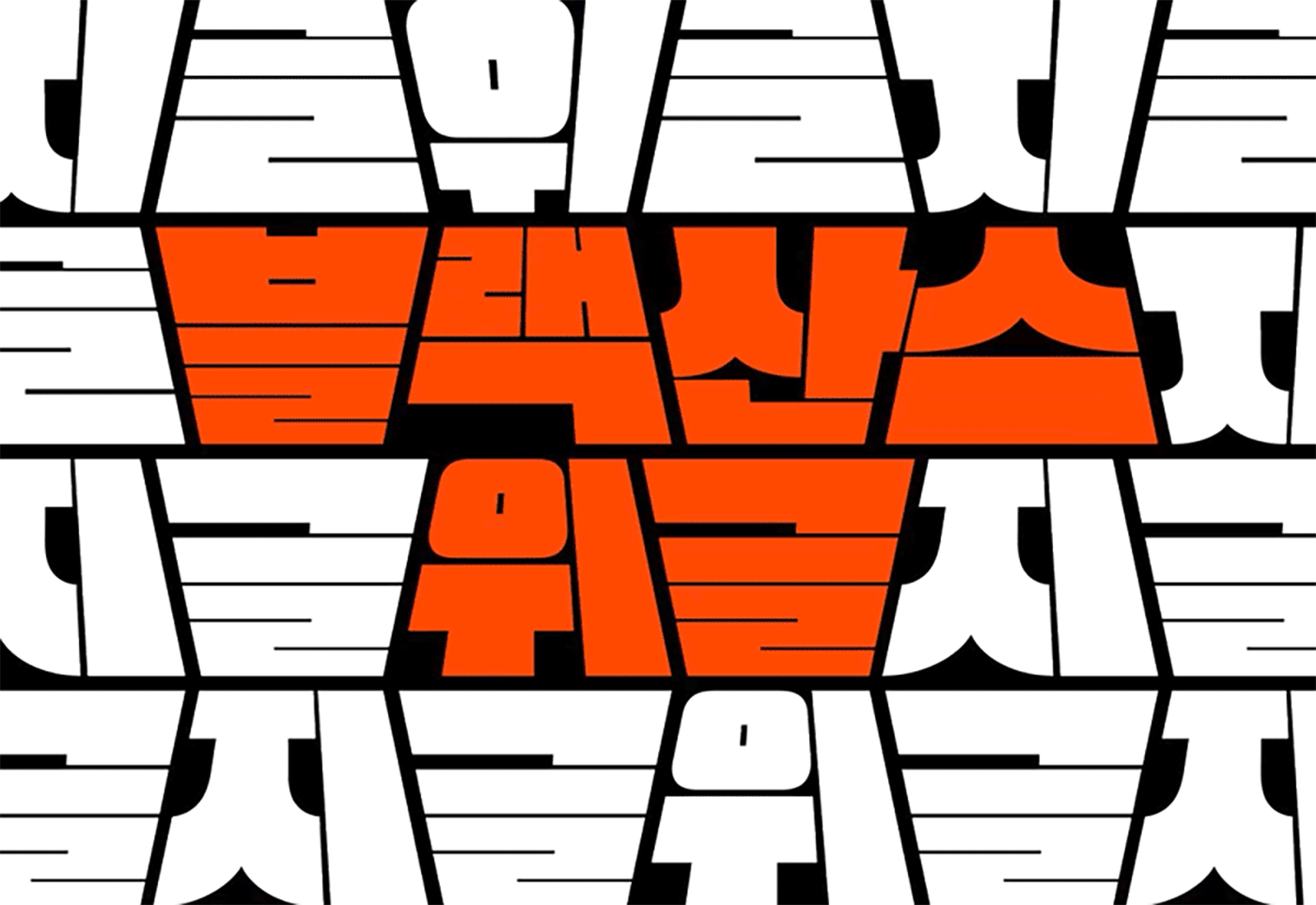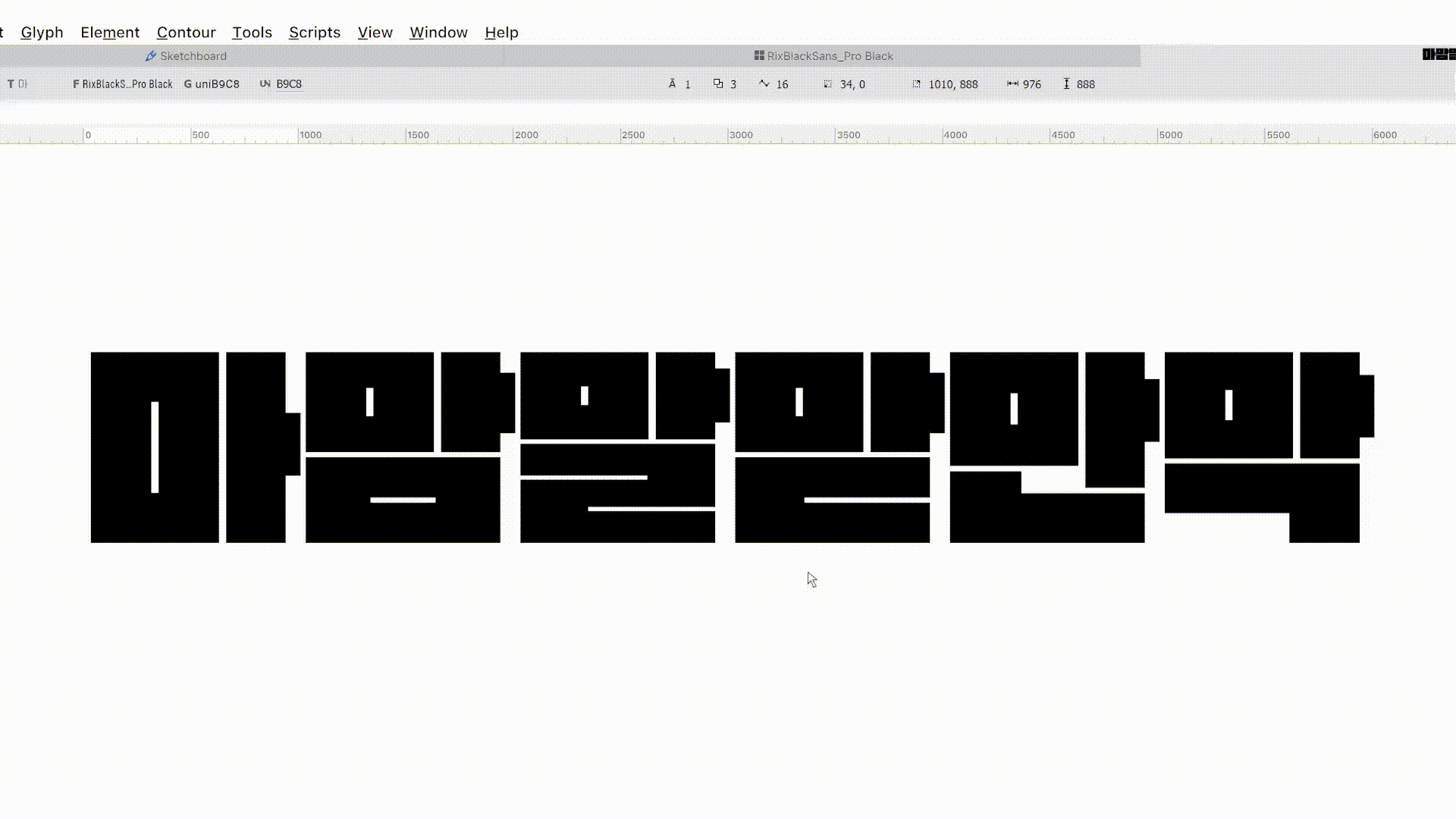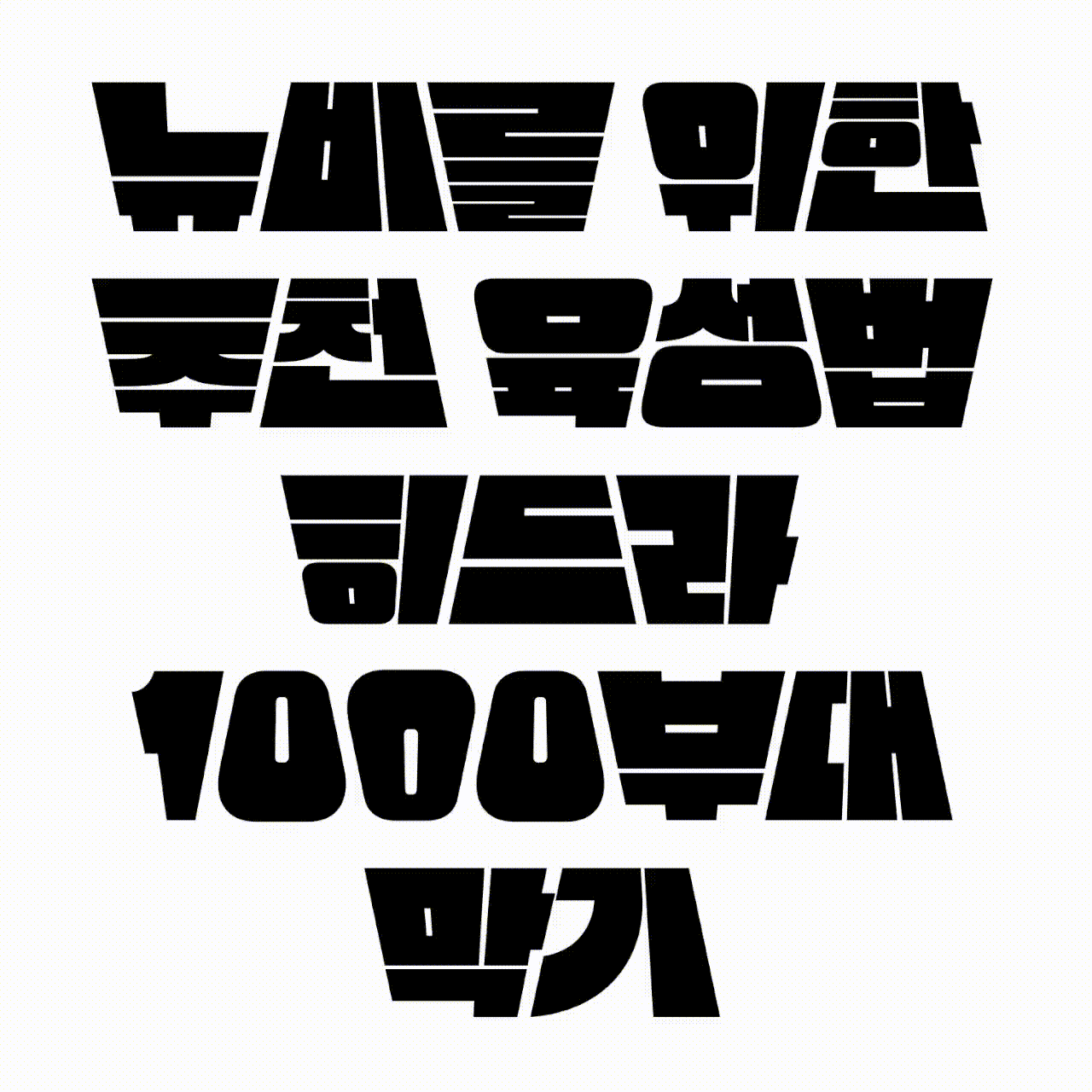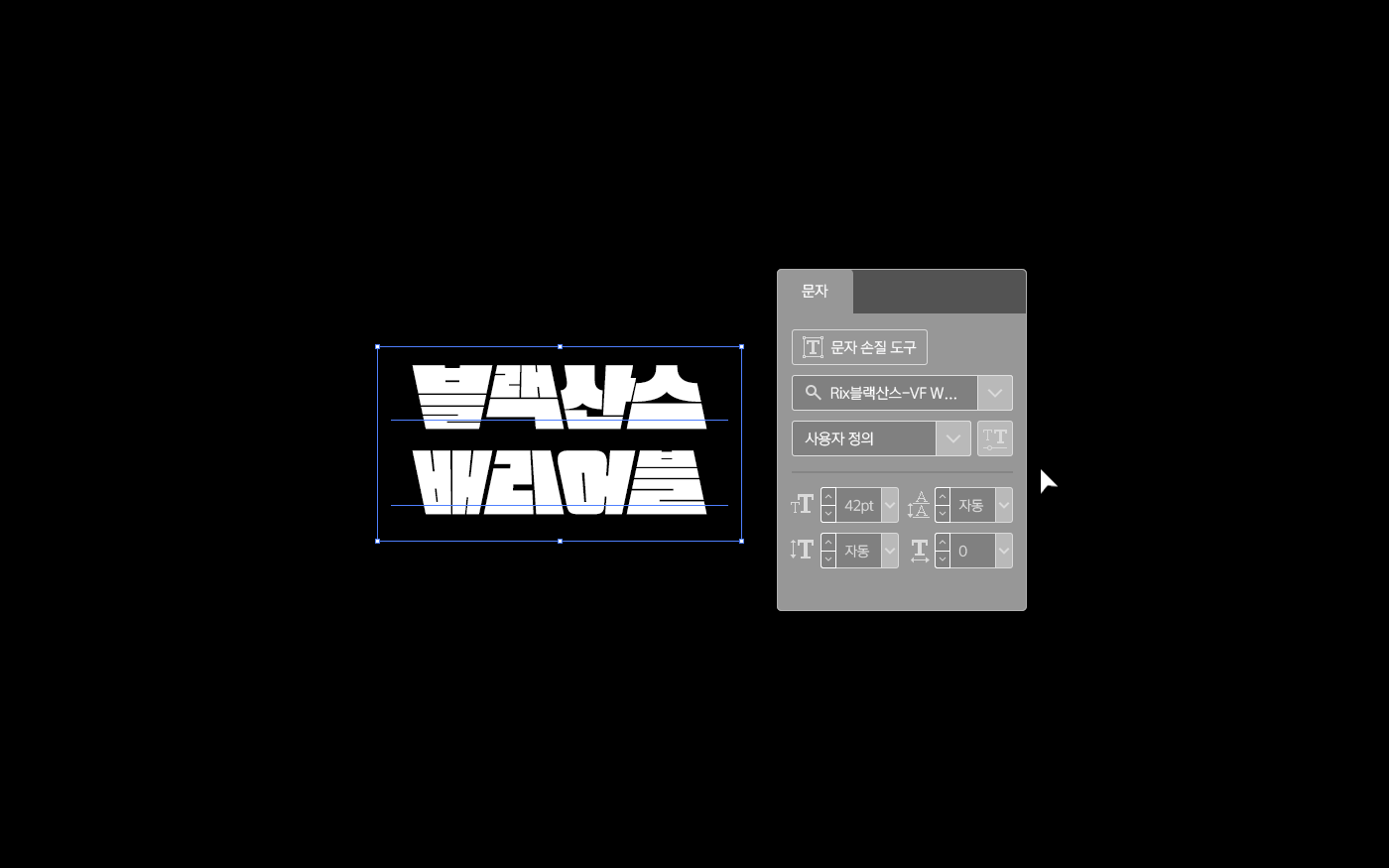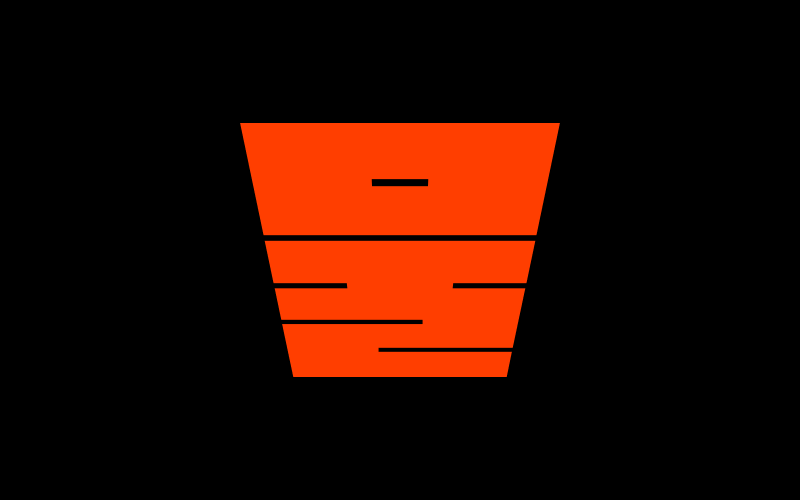
안녕하세요. 오늘은 위트 있고 강렬한 매력을 가진! 10월의 신서체「Rix블랙산스-VF Wiggle」을 소개합니다. 제목용 서체로 여전히 많은 사랑을 받고 있는 Rix블랙산스에서 변형을 준 서체인데요. 배리어블 축을 통해 사용자가 직접 글자의 속성을 조절하여 하나의 폰트로 다양한 형태를 구현할 수 있는 폰트입니다. 이번 블랙산스배리어블의 제작을 맡으신 박민우 디자이너와의 인터뷰를 통해 폰트에 대해 더 자세히 알아볼게요 :)
안녕하세요! 이번 10월 신서체 Rix블랙산스배리어블 Wiggle을 담당한 박민우입니다. 처음 인사드리네요!
처음으로 제작을 맡으신 폰트라고 들었어요. 어떤 과정이 있었나요?
네 맞습니다, 시작은 동료 디자이너님이 제작한 Rix힘을내요 였습니다. 역삼각형 글자 틀이 재미있는 폰트인데, 보다 보니 이 기울기가 한 방향이 아니라 반대 방향으로 번갈아 반복된다면 개성 있는 인상을 줄 것 같다는 영감을 받았거든요. 발상을 한 뒤로 Opentype 기능을 공부하며 고민하다가, Opentype 문맥 대체 기능을 활용해 구현이 가능함을 확인하고 작업을 시작했습니다. 변형되는 글자 틀을 강조해서 보여주기 위해 네모 틀에 꽉꽉 들어찬 모듈의 Rix블랙산스를 베이스로 선택했고, 파이썬으로 글리프의 활자면 자체에 원근 변환을 주어 외곽선을 조정하는 스크립트를 개발했습니다. 스크립트 적용 이후 라틴과 약물 오류를 수정해 디자인을 마무리했습니다.
Rix블랙산스-VF Wiggle 폰트에 대해 더 자세히 알려주세요!
Rix블랙산스-VF Wiggle은 반대 기울기의 사다리꼴 글자 틀이 번갈아 가며 타이핑되는 특이한 인상의 폰트입니다. 블랙산스의 까맣고 묵직한 인상을 유지하면서도, 들쑥날쑥한 기울기가 만드는 리듬감으로 눈길을 끄는 재미있는 글줄을 만들 수 있습니다. 배리어블 폰트로 제작했기 때문에 수치 조절을 통해 반대 방향의 글자 틀 사이에서 사용자가 원하는 만큼 변형 정도를 설정할 수 있답니다!
이 폰트를 어디에, 어떻게 쓰면 좋을까요?
네모 틀에 꽉꽉 들어찬 아주 무거운 폰트이기 때문에 단어 단위 짧은 호흡의 제목 용도로 유용할 것 같아요. 빠르게 지나가게 되는 동영상 썸네일 등의 맥락에서도 번갈아 바뀌는 기울기의 리듬감이 사람들의 시선을 확! 잡아 끌 수 있지 않을까 생각합니다.
이렇게 첫 폰트를 제작해 본 소감!
기존 원도를 기반으로 자형을 조정한 폰트다 보니 디자인적으로는 고민할 지점이 많지 않았지만, 직접 외곽선을 그리는 일 외의 다른 부분에서 배운 점이 많았어요. Opentype 기능 적용이나 배리어블 폰트 제작, 파이썬 스크립트 개발까지… 직접 겪기 전에는 생각하지 못했던 폰트 개발의 다른 측면을 경험한 것 같습니다. 이번 블랙산스배리어블에 모두 적용된 것은 아니지만, 새로운 기술의 공부도 재밌더라고요. 이런 여러 방향 모두 능숙한 다재다능한 디자이너로 성장하고 싶습니다😊 물론 직접 그리는 다른 폰트도 준비 중이니까요, 금방 들고 와서 새로 인사드리겠습니다. 조금만 기다려주세요. 감사합니다!!
인상파 블랙산스, 재미를 더하다
Rix블랙산스는 2019년에 출시되었던 제목용 서체로, 최대 굵기를 사용하여 속 공간의 하얀 면 사이 속 공간으로 글자 사이를 구분하여 표현한 강한 인상의 폰트입니다.
정사각형의 네모꼴 구조, 직선적인 디자인의 단단한 이미지가 눈길을 끌어 홍보물, 배너, 도서 등 다양한 콘텐츠에 활용되고 있는데요. 이번에 형태의 틀을 깨며 위트 있는 변신(?)을 하게 되었습니다.
두꺼운 웨이트가 특징인 블랙산스에게는 아주 큰 변화라고 할 수 있을 것 같아요. 글자의 형태가 네모틀을 벗어나 사다리꼴로 변형이 일어나고 또 앞뒤로 번갈아가며 효과가 적용됩니다.
위트 있는 기울기와 반복성
각도가 변화하는 Rix블랙산스-VF Wiggle은 배리어블 축을 이동함에 따라 상하 글자 폭이 달라집니다. 사다리꼴 글자틀에도 서체가 잘 읽힐 수 있는 가장 적절한 기울기를 설정했습니다.
사다리꼴 모듈로 글씨가 반복적으로 타이핑되며 재미를 줍니다. 두껍고 묵직한 느낌이 강했던 기존의 Rix블랙산스에서 역동적이고 위트 있는 이미지로 표현되었어요🥊
배리어블 기능은 영문, 일어와 숫자 및 약물에도 적용되어 국문과 자연스럽게 혼용하여 쓸 수 있습니다. 개성 강한 디자인으로 다양하고 폭넓은 콘텐츠에 활용 가능합니다.
| 이렇게 활용해 보세요
위트 있고 강렬한 사선 디자인으로 시선을 끌어주어 타이틀에 활용하기 좋고, 흔히 볼 수 있는 서체들과 다른 유니크함을 상품과 결합하여 녹여낼 수 있습니다. 짧은 텍스트나 영상 썸네일 등 주목도가 필요한 콘텐츠에 사용해 보세요!